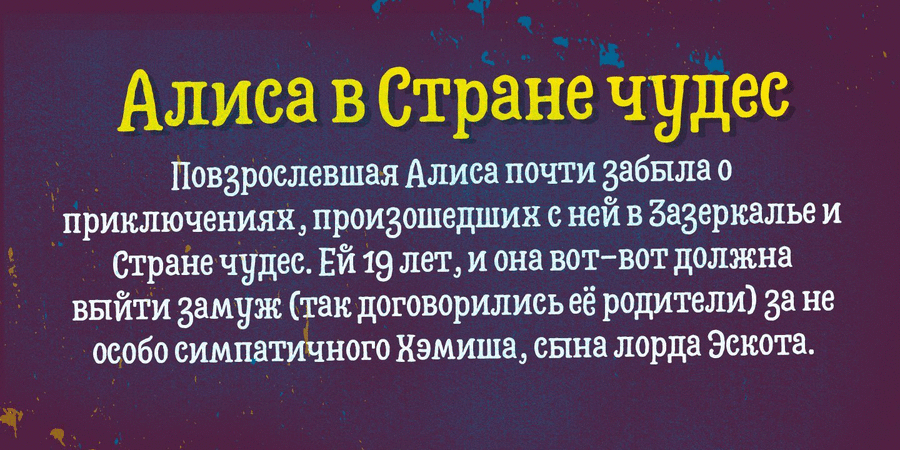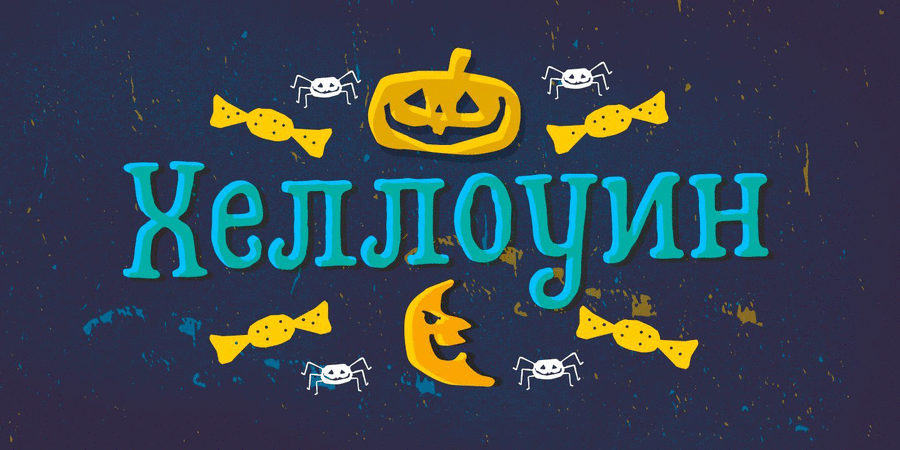
Hatter, шрифт Божевільного Капелюшника – це найгелловїнськіший шрифт у світі! Він є гримучею сумішшю брускової антикви дев'ятнадцятого століття й леттерінгу в стилі фільмів Тіма Бертона: Аліса в Країні Чудес, Труп Нареченої, Кошмар перед Різдвом тощо. Шрифт одночасно нагадує моторошного Франкенштейна й молоду відьму.
Hatter містить латиницю та кирилицю, тому їм можна лякати людей майже по всьому світі! =)
Шрифт закликали до життя Родріго Арая Салас та Андрій Кудрявцев під повним місяцем у п'ятницю 13-го 2017 року.